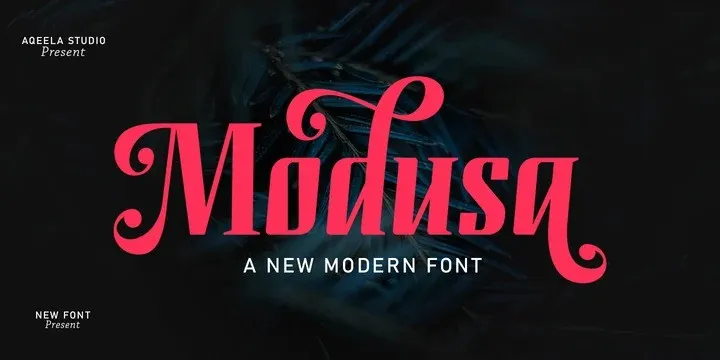
Modusa Font – Download Grátis
A Modusa Font é uma elegante serif que resgata os velhos truques do tipo typográfico moderno. Inspirada na temática mitológica, ela se destaca com seus sinuosos e únicos traços serifados. Arkyn é mais do que simplesmente um tipo de texto; possui alternativas e ligaturas, criando uma riqueza em suas possibilidades. Desenvolvida para inspirar os criativos a alcançarem níveis inimagináveis de originalidade e elegância. Seja você um designer de arte digital ou gráfico, essa fonte tem o potencial de transformar seus projetos de ideias geniais em obras de arte perfeitas.